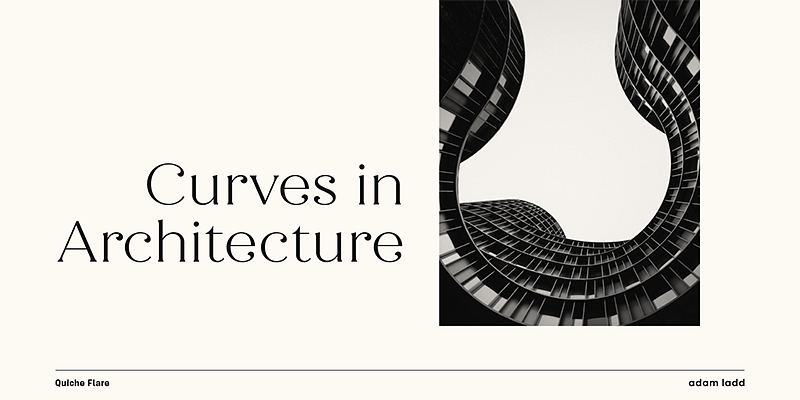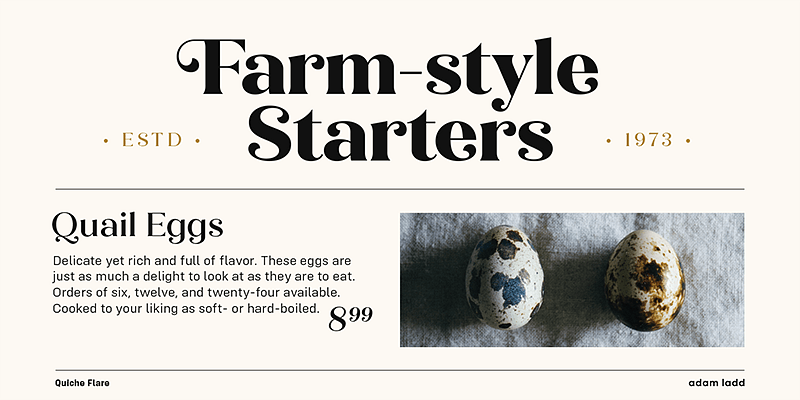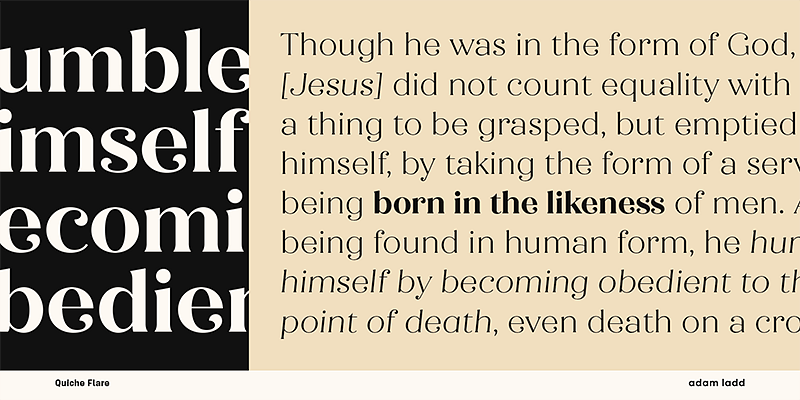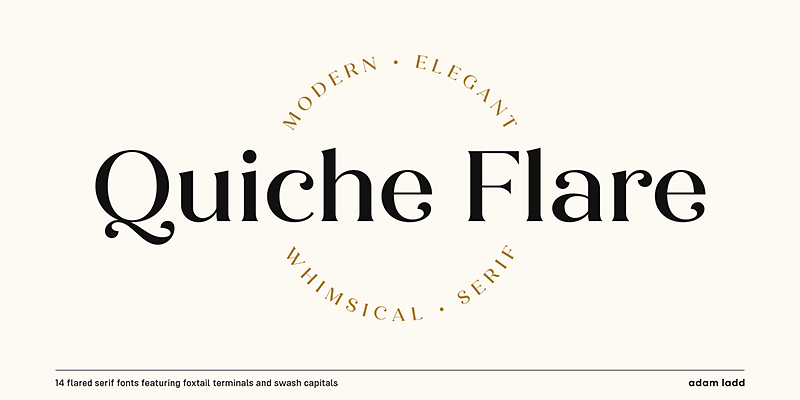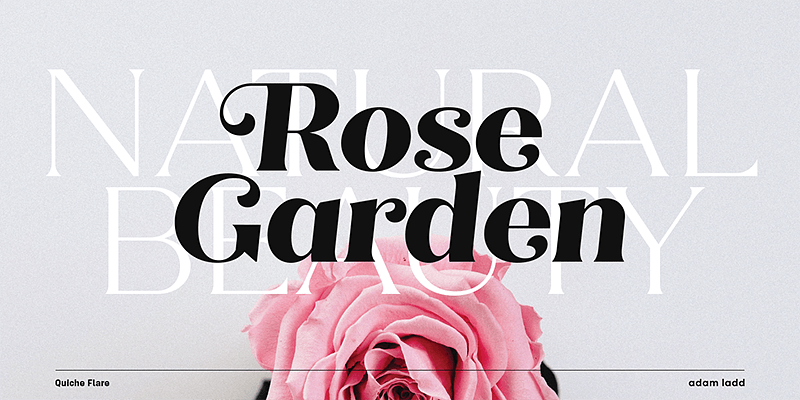
Parce qu’il aime imaginer des typographies à la fois utiles et uniques, Adam Ladd crée des polices attractives et variées, sans empattement, avec empattement ou scriptes, qui vont du charme vintage à l’esthétique moderne. Son expérience en tant que directeur artistique auprès de deux des magazines de design les plus prestigieux (HOW et PRINT) façonne son travail de typographe. Ses polices ont été achetées aussi bien par des particuliers que par de grandes entreprises de différents secteurs, parmi lesquelles Disney, Whole Foods, Blizzard Entertainment et Penguin Random House.